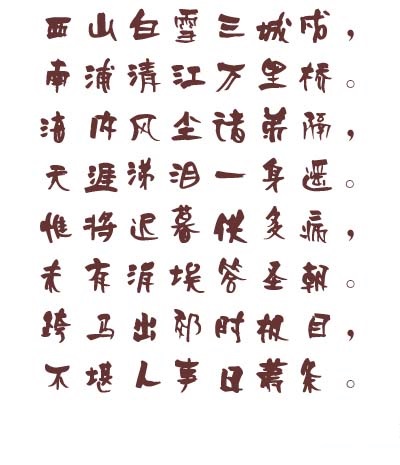
軟件介紹 軟件標簽: 葉根友字體 葉根友風帆特色簡體共有中文漢字6763個以及其他英文字母和阿拉伯數字,為葉根友先生于2008年所創(chuàng)作,喜歡這款字體的朋友們快來下載吧!字體介紹:葉根友風帆特色字體是一款以帆船的造型來設計,風格獨特,寓意深遠,整個字體向右傾斜,字體富有更新的書法創(chuàng)新思維,不落俗套。在筆畫對稱學中屬于是一種不走尋常思維的漢字字體創(chuàng)意,融合了中國書法黃金分割法則的側重理念。安裝說明:如果您是Win7用戶直接右鍵選擇安裝即可,其他系統(tǒng)的用戶可以將字體文件復制到C:\Windows\Fonts文件夾即可完成安裝相關推薦:system.data.common.dll文件 授權:免費軟件 WinAll, WinXP, Win7大?。?6KB語言:中文system.data.common.dll是windows系統(tǒng)中非常重要的dll文件,當你的計算機提示“system.data.common.dll丟失”或者“system.data.common.dll錯誤”,就會影響一些游戲和軟件無法正常運行,這時只需在本站下載該文件放下載地址 軟件截圖 上一張下一張(1 / 1) 安裝詳細截圖 猜你喜歡 葉根友 葉根友 葉根友字體是現(xiàn)代社會中使用最為廣泛的字體,包含葉根友疾風草書、葉根友刀鋒黑草等,現(xiàn)綠色資源網小編整合幾款葉根友字體大全供用戶下載,歡迎到綠色資源網體驗! 查看更多>> 葉根友哲在手寫字體 4.00M/中文/6.0/官方版下載 葉根友離賢行書字體 10.00M/中文/5.7/免費版下載 南構字體合集 50.00M/中文/3.7/共16款下載 南構汪本友行書字體 10.00M/中文/3.3/下載 南構標羽歌士體 10.00M/中文/5.0/免費版下載 南構王天喜行書簡體字體 10.00M/中文/2.1/下載 其他版本下載 標題 大小 更新日期 下載 下載地址 電腦版 葉根友風帆特色簡體 免費官方版 點擊報錯 軟件無法下載或下載后無法使用,請點擊報錯,謝謝! 關閉報錯反饋 請描述您所遇到的錯誤,我們將盡快予以修正,謝謝! *必填項,請輸入內容 本類最新 葉根友字體庫打包 共18款 葉根友風帆特色簡體 免費官方版 葉根友哲在手寫字體 官方版 南構村花手寫體ttf版 南構王小花手寫ttf常規(guī) 南構日漫風字體 相關文章 三星i9100點心rom下載地址及rom特色介紹 中興V880基于 CM9 最新 4.0.4 測試版rom下載及rom特色介紹 用戶評論 熱門評論 最新評論 發(fā)表評論 查看所有評論(0) 昵稱: 請不要評論無意義或臟話,我們所有評論會有人工審核. 字數: 0/500 (您的評論需要經過審核才能顯示)